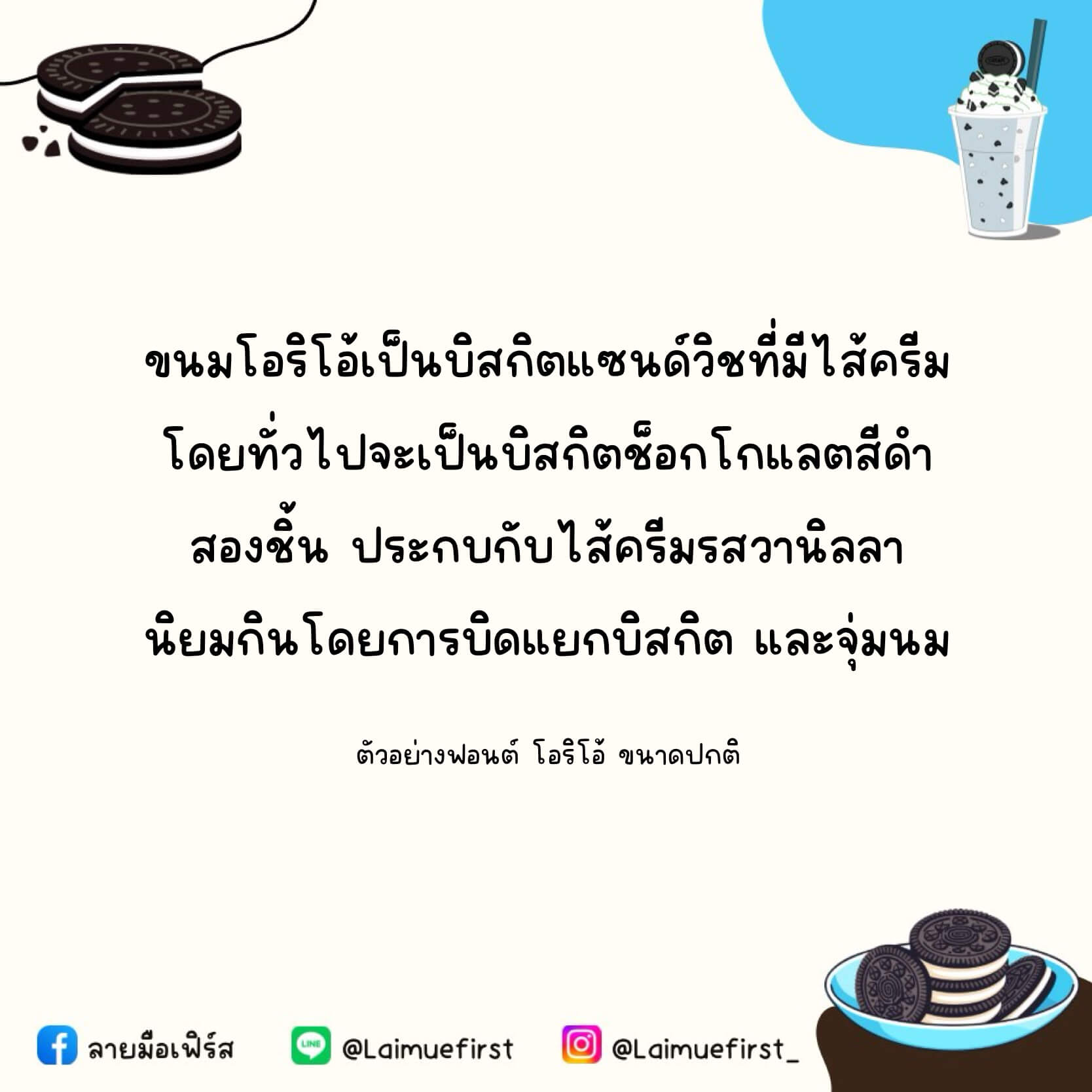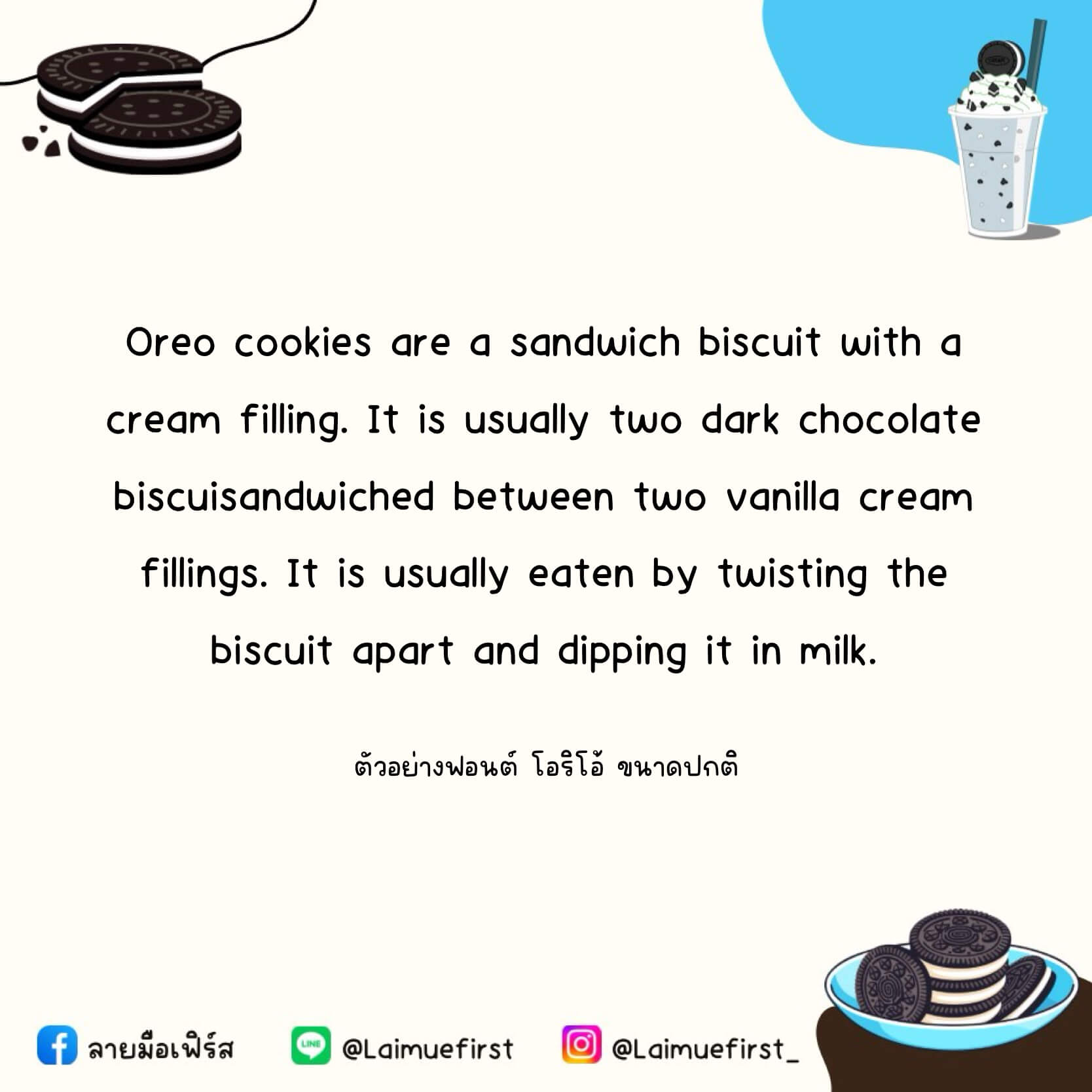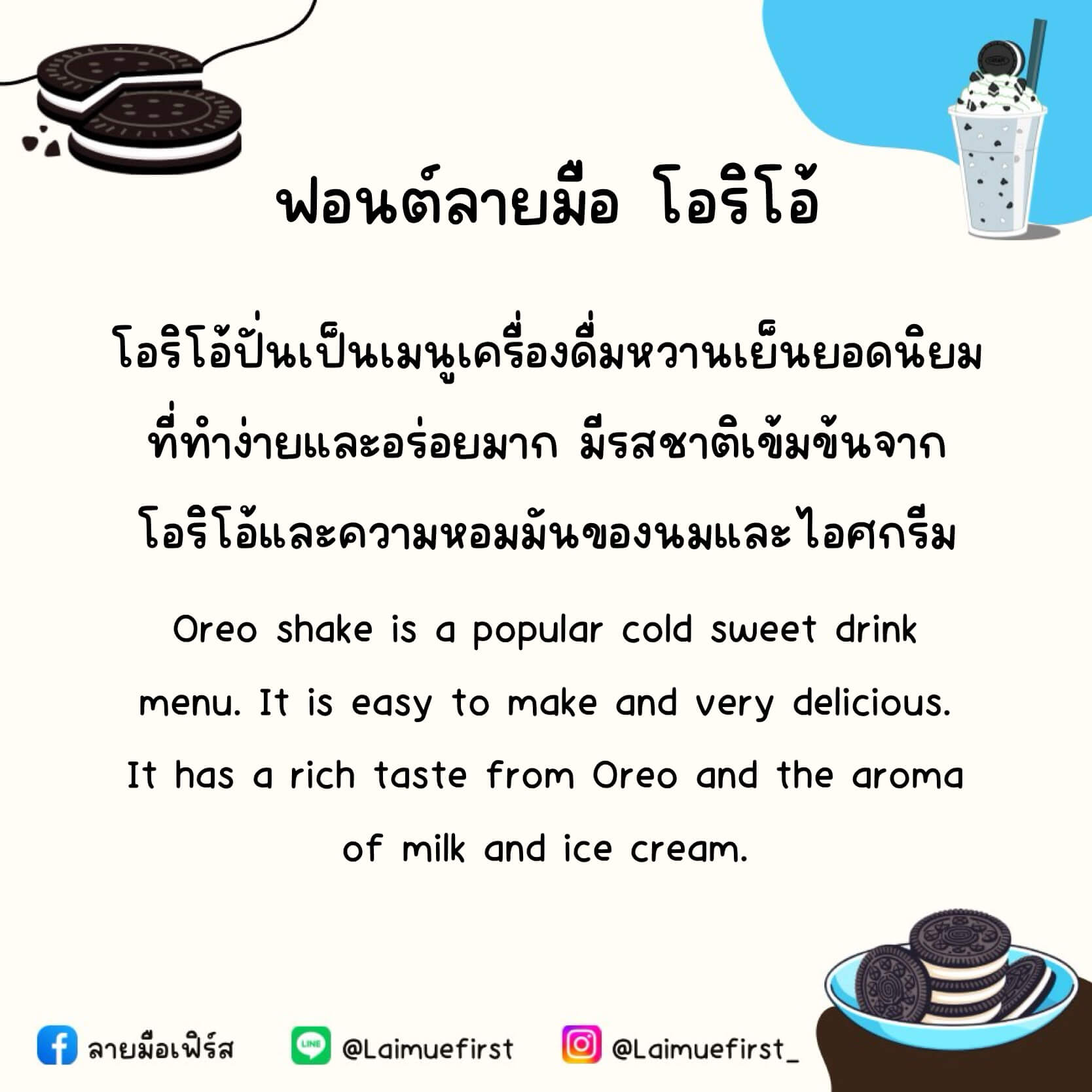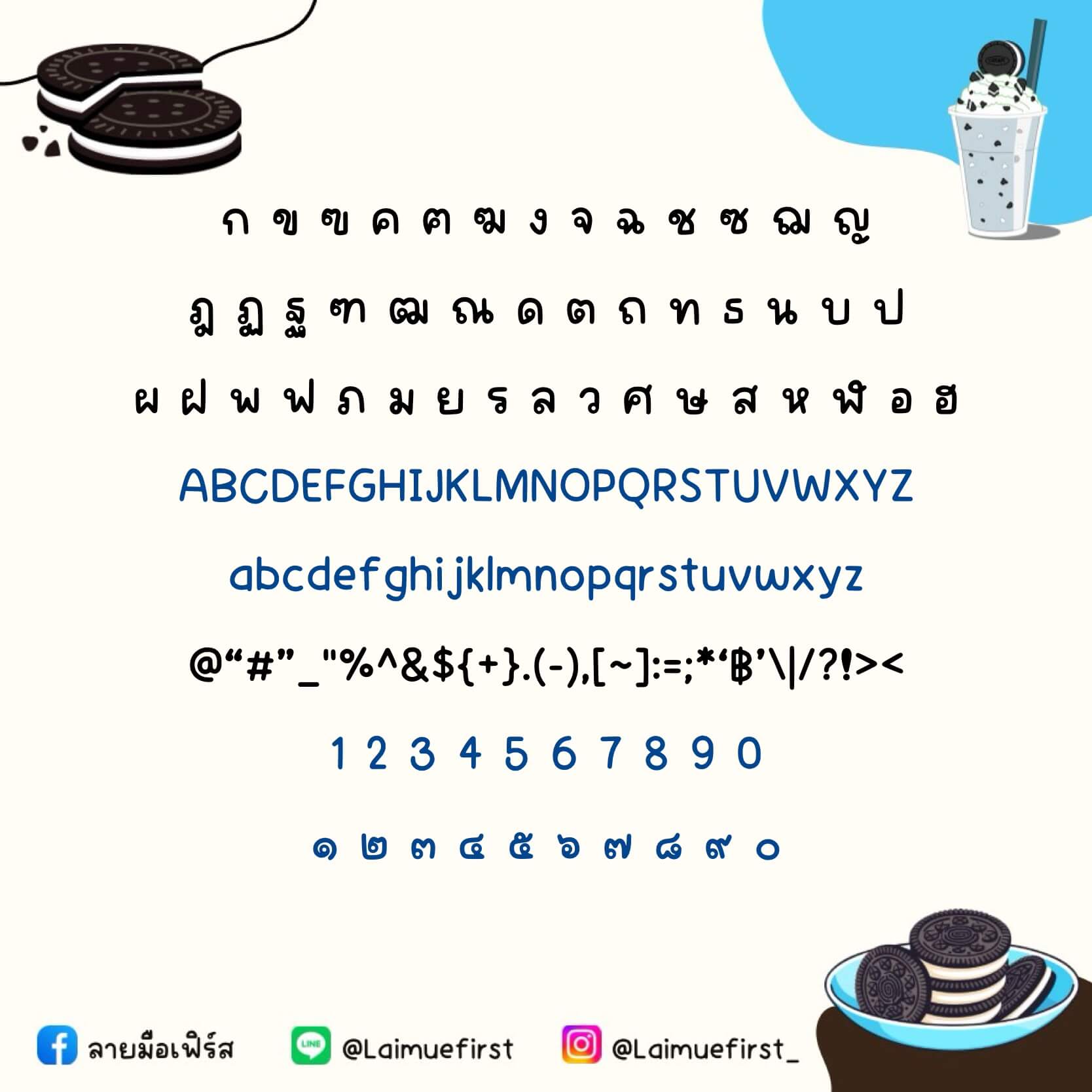
โอริโอ้ (LMF Oreo)
ฟอนต์ลายมือ โอริโอ้ (LMF Oreo) แจกฟรี สำหรับทดลองใช้งานแบบส่วนตัว (Demo)
ไฟล์เวอร์ชันทดลองใช้งาน (Demo) ตัวอักษรจะมีขนาดหนา-บางไม่เท่ากัน